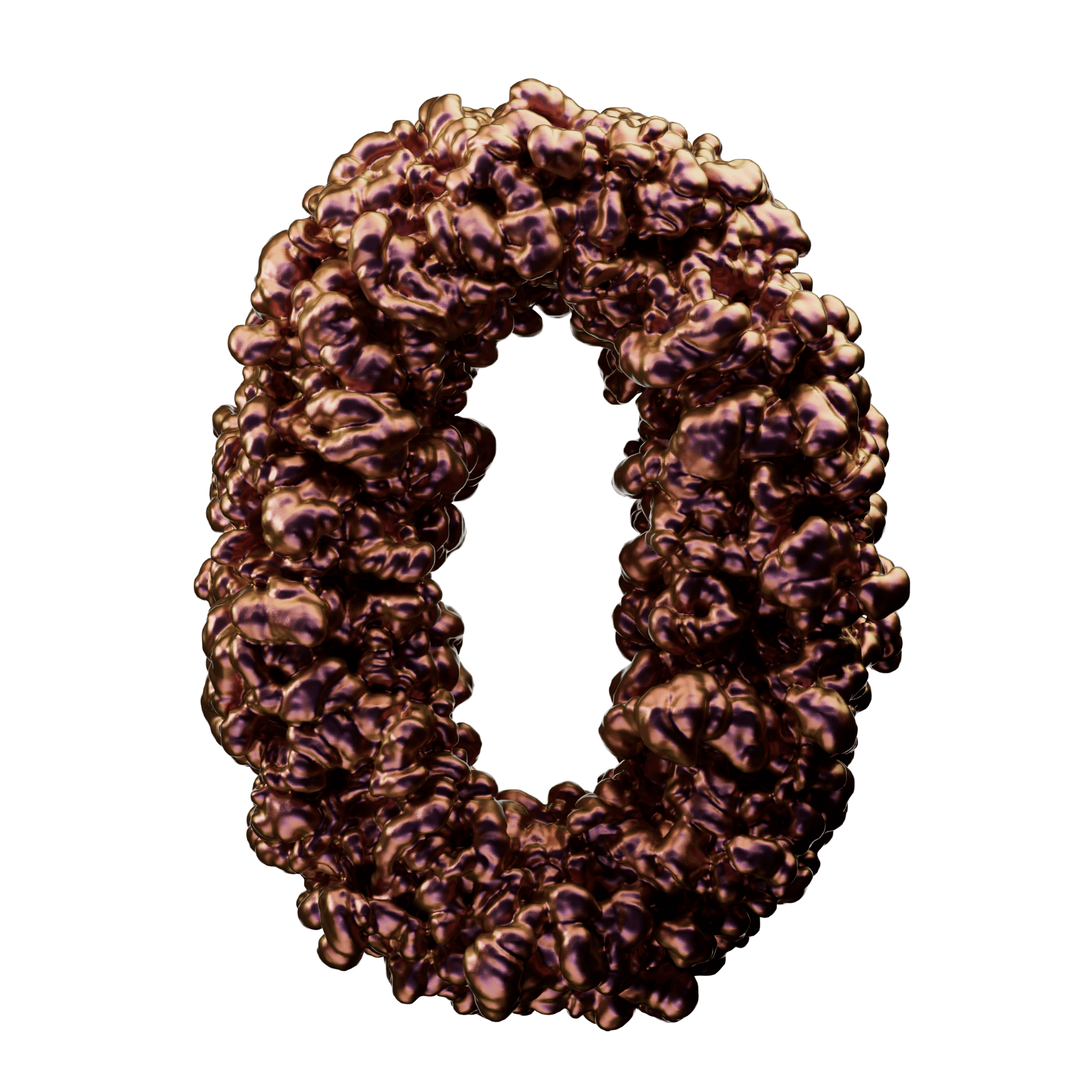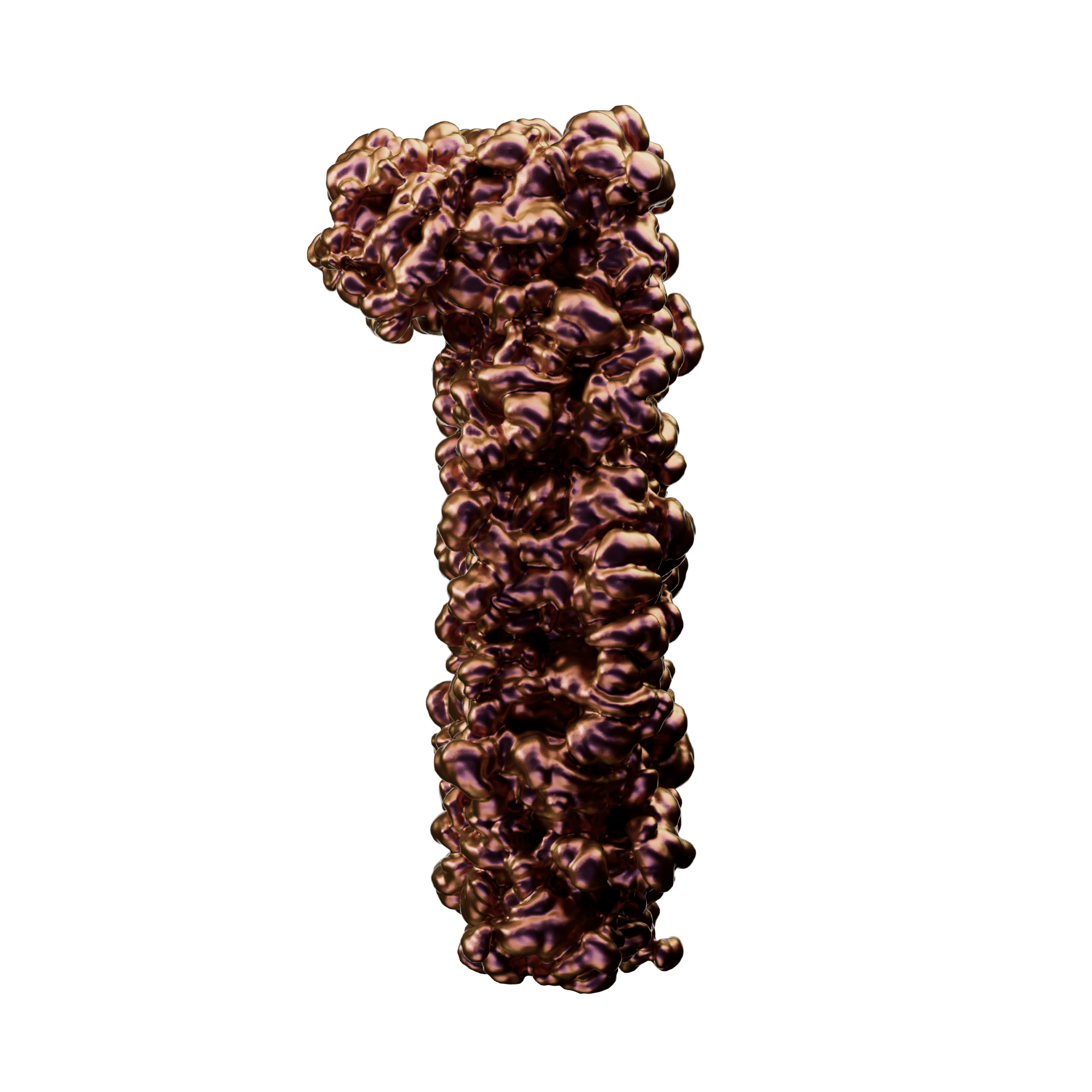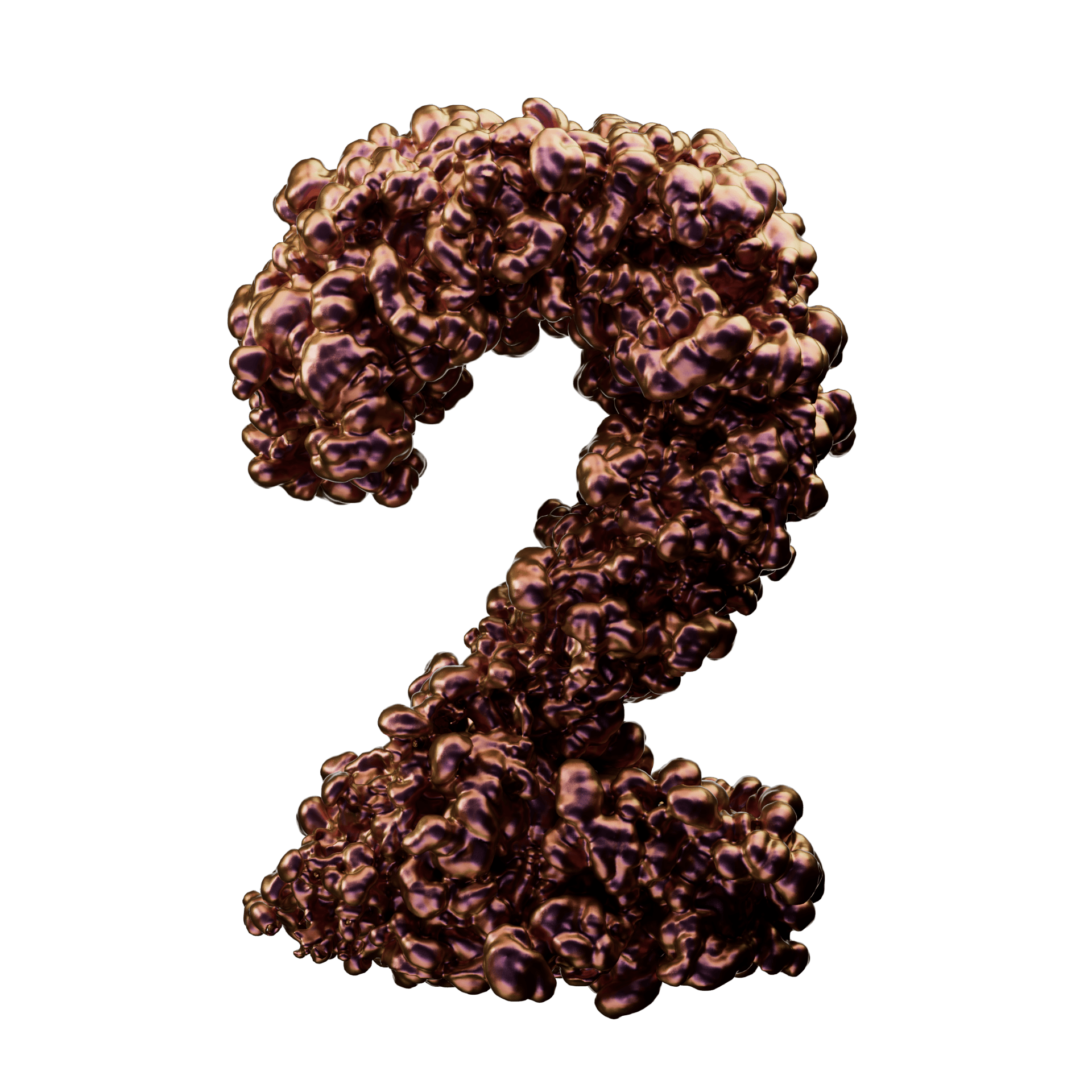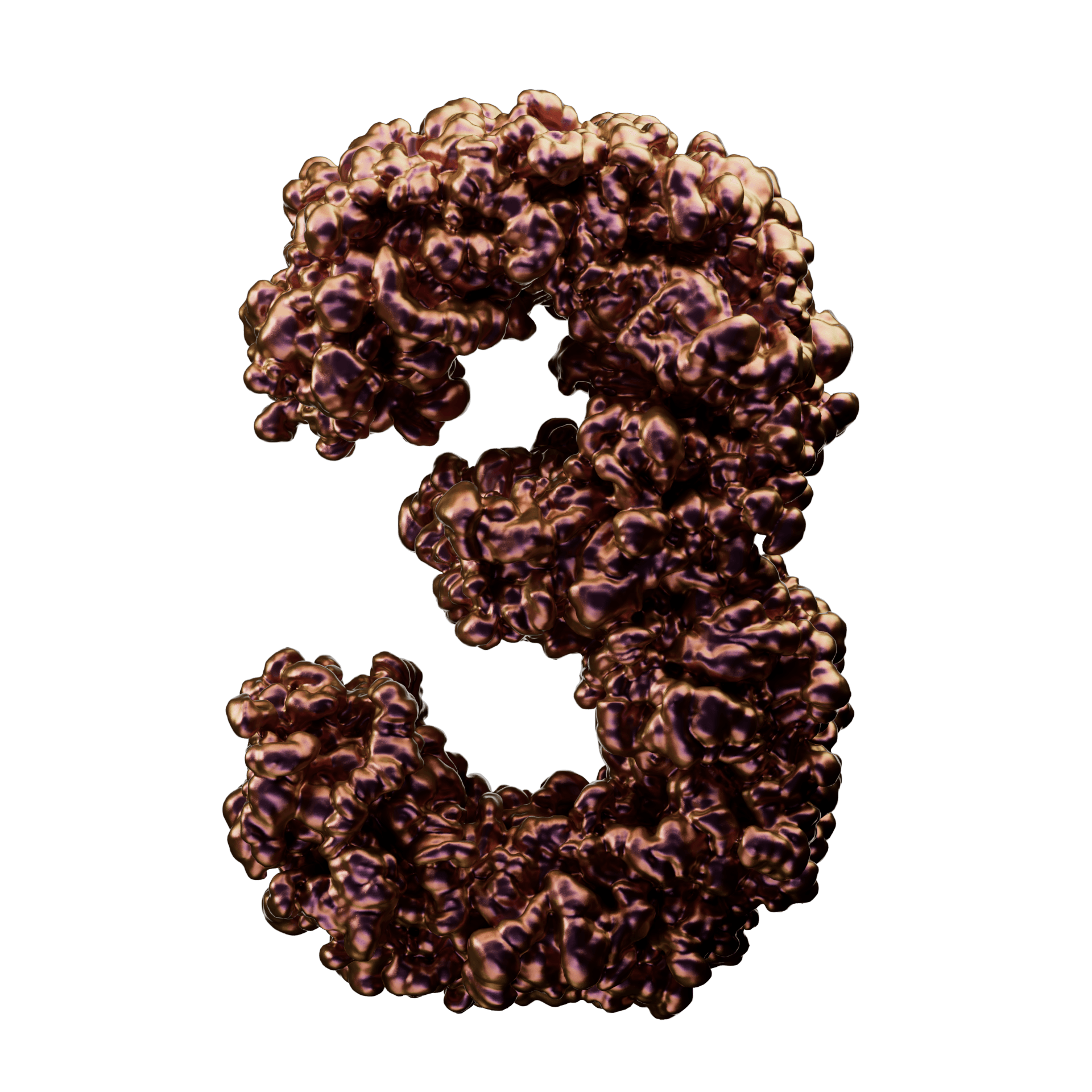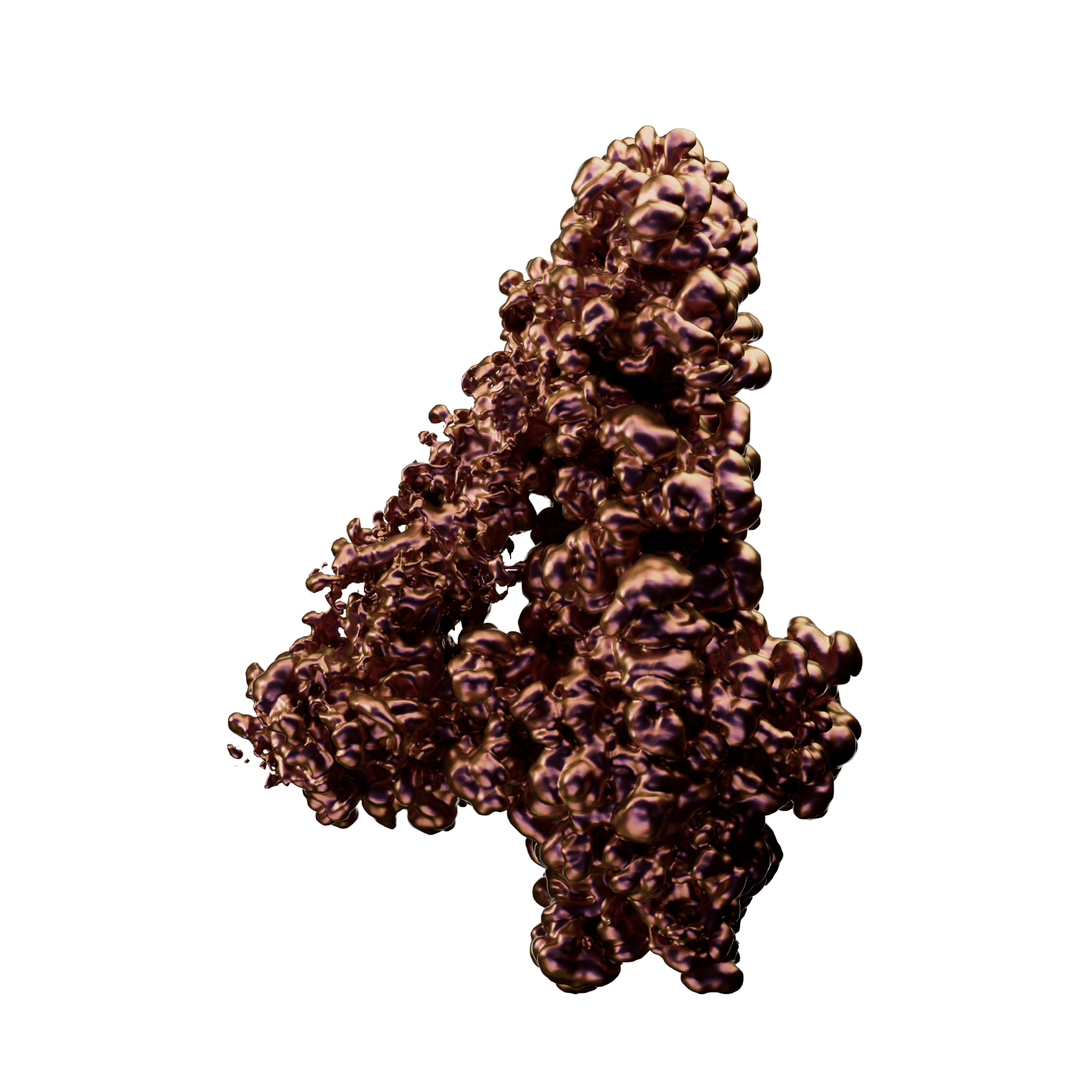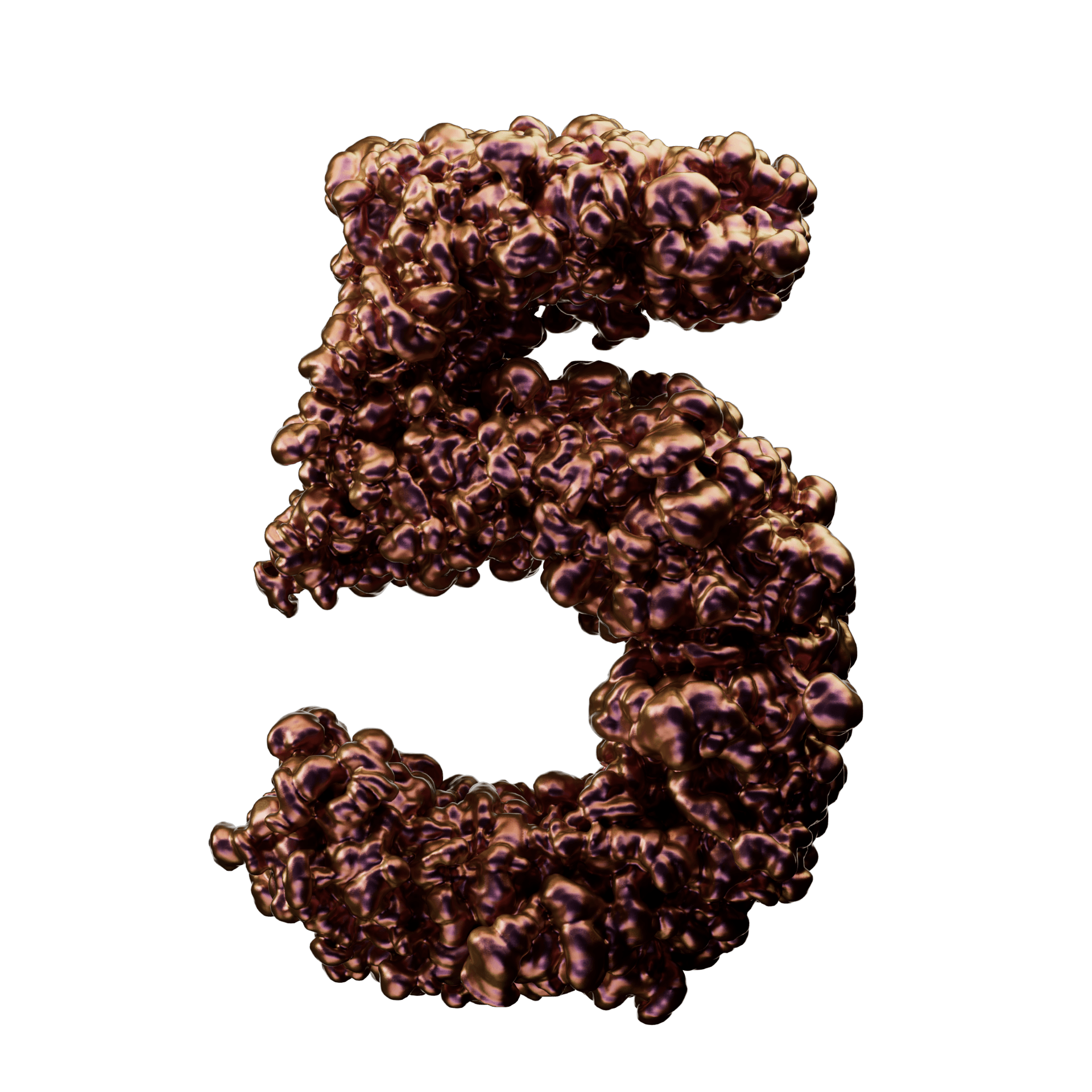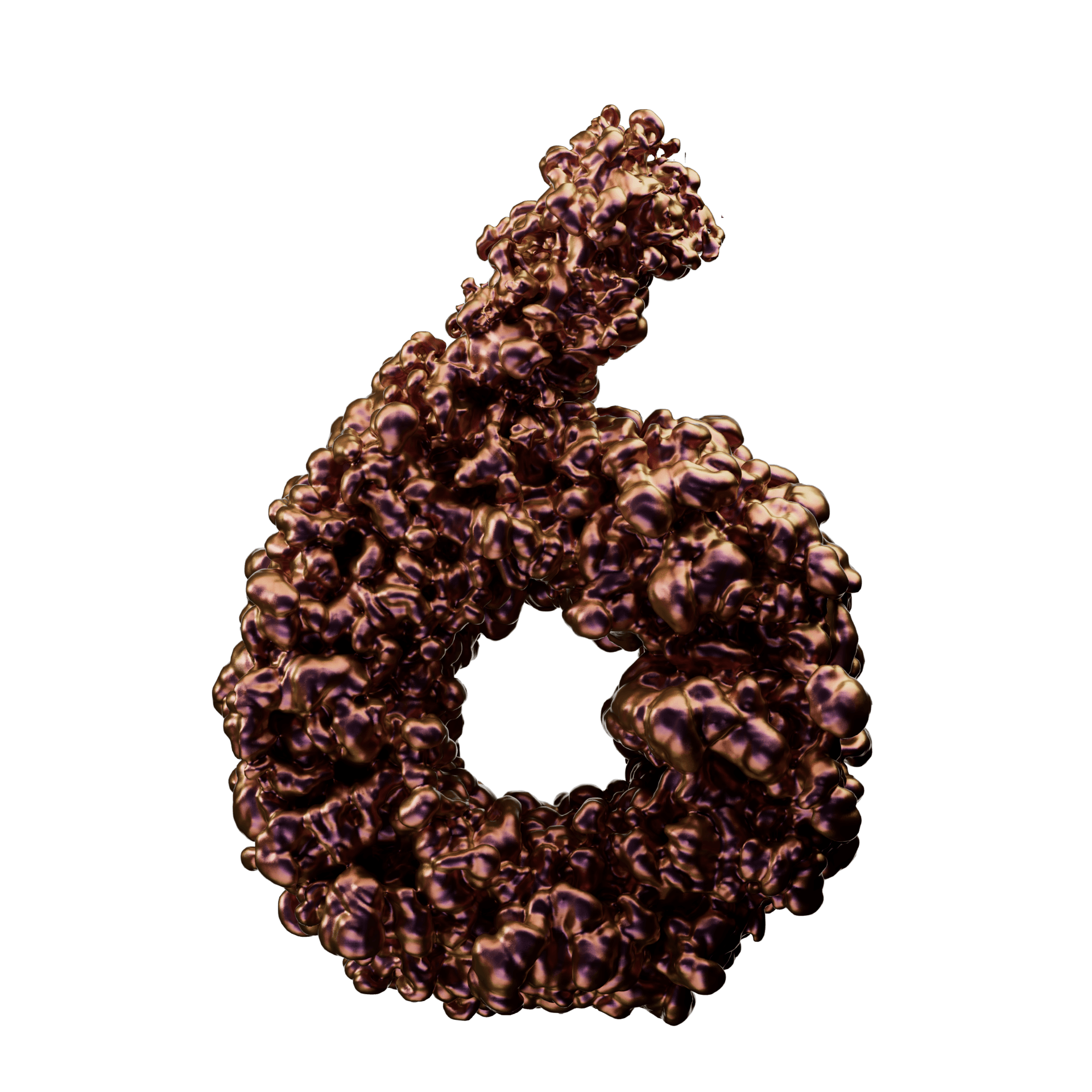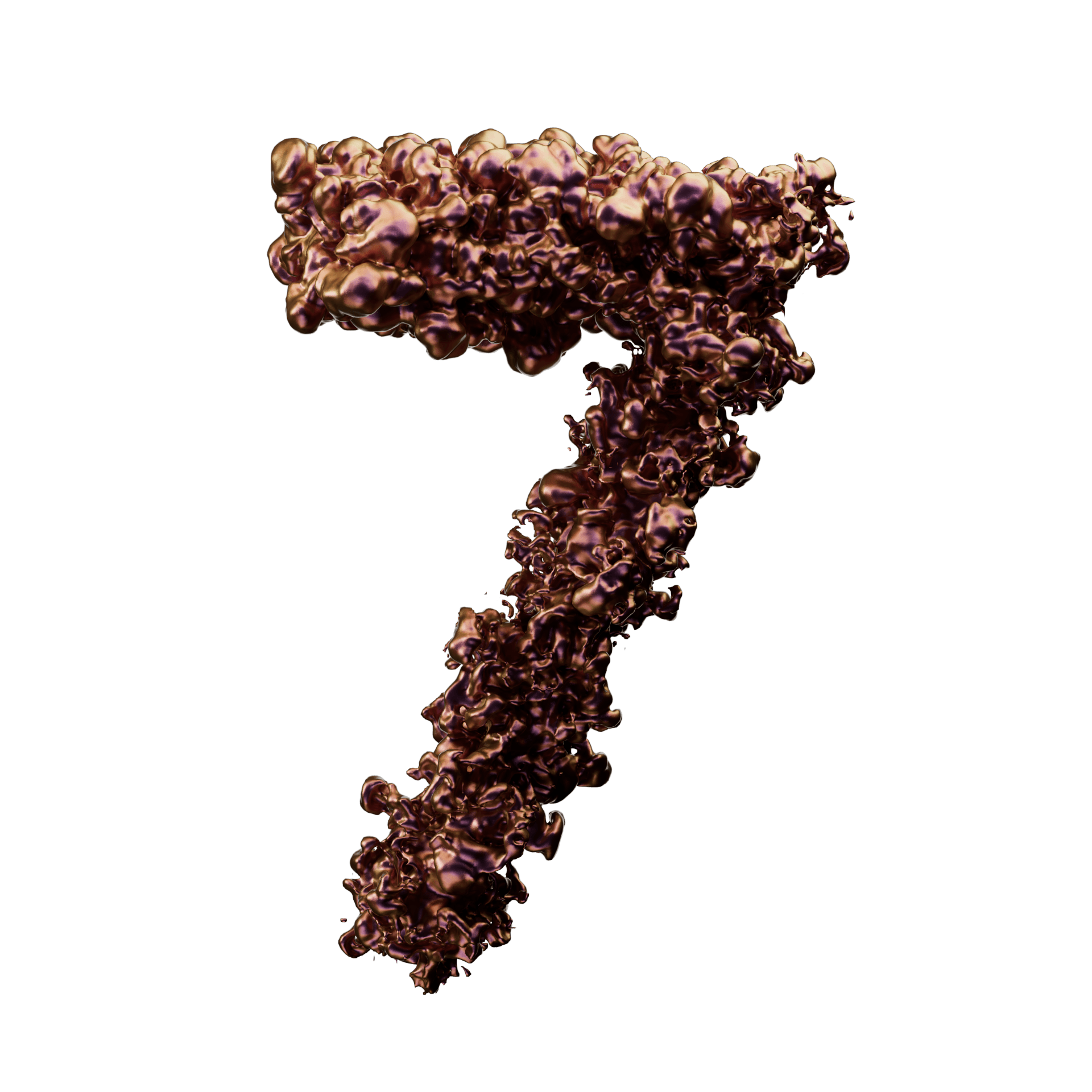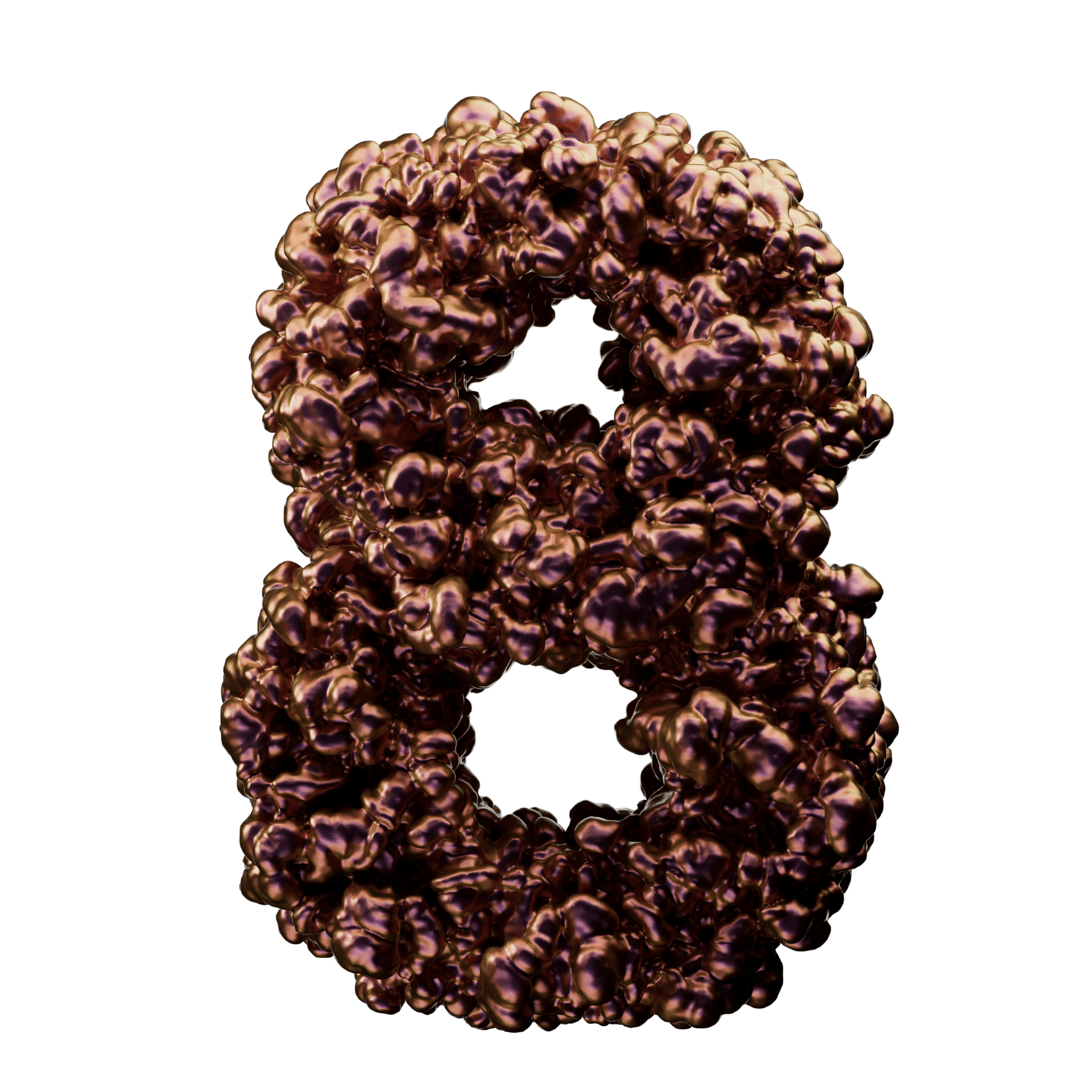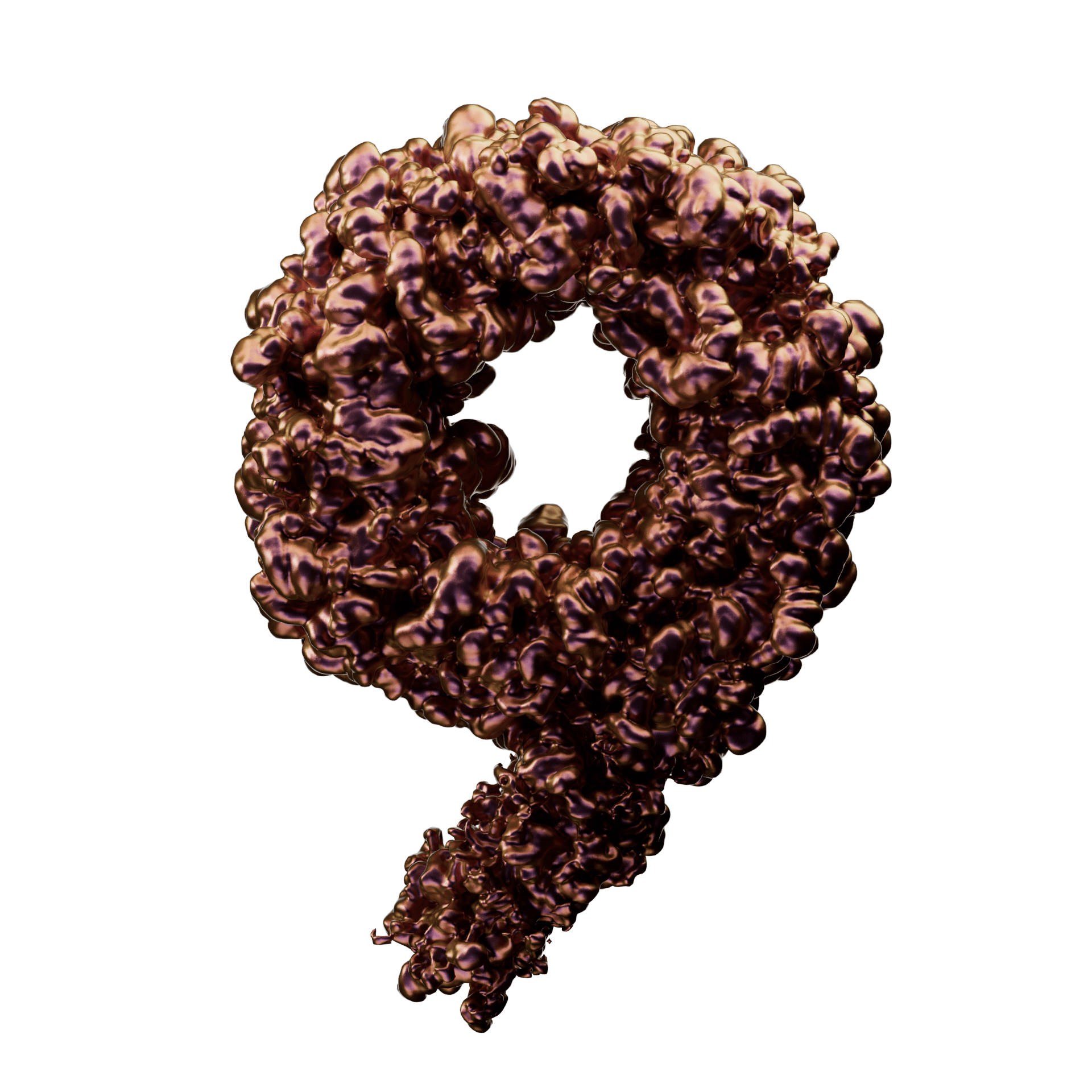
Growth Type
Simulación orgánica, Cinema 4D, X-Particles
Año2024
Growth Type es un alfabeto 3D orgánico: el glifo como colonia. Una simulación de X-Particles nace dentro de la letra y se expande hasta formar una masa nodular densa — cobre iridiscente que vira a púrpura — que conserva la estructura del carácter como andamiaje mientras la superficie adquiere una lógica propia. Hecho con Cinema 4D, X-Particles y Redshift: cuatro vídeos de la letra F y 36 caracteres, de la A a la Z y del 0 al 9.
F
A — Z
Carácter A de Growth Type: letra 3D de cobre iridiscente con textura nodular, nacida de una simulación de X-Particles, sobre fondo negro
Carácter B de Growth Type: letra 3D de cobre iridiscente con textura nodular, nacida de una simulación de X-Particles, sobre fondo negro
Carácter C de Growth Type: letra 3D de cobre iridiscente con textura nodular, nacida de una simulación de X-Particles, sobre fondo negro
Carácter D de Growth Type: letra 3D de cobre iridiscente con textura nodular, nacida de una simulación de X-Particles, sobre fondo negro
Carácter E de Growth Type: letra 3D de cobre iridiscente con textura nodular, nacida de una simulación de X-Particles, sobre fondo negro
Carácter F de Growth Type: letra 3D de cobre iridiscente con textura nodular, nacida de una simulación de X-Particles, sobre fondo negro
Carácter G de Growth Type: letra 3D de cobre iridiscente con textura nodular, nacida de una simulación de X-Particles, sobre fondo negro
Carácter H de Growth Type: letra 3D de cobre iridiscente con textura nodular, nacida de una simulación de X-Particles, sobre fondo negro
Carácter I de Growth Type: letra 3D de cobre iridiscente con textura nodular, nacida de una simulación de X-Particles, sobre fondo negro
Carácter J de Growth Type: letra 3D de cobre iridiscente con textura nodular, nacida de una simulación de X-Particles, sobre fondo negro
Carácter K de Growth Type: letra 3D de cobre iridiscente con textura nodular, nacida de una simulación de X-Particles, sobre fondo negro
Carácter L de Growth Type: letra 3D de cobre iridiscente con textura nodular, nacida de una simulación de X-Particles, sobre fondo negro
Carácter M de Growth Type: letra 3D de cobre iridiscente con textura nodular, nacida de una simulación de X-Particles, sobre fondo negro
Carácter N de Growth Type: letra 3D de cobre iridiscente con textura nodular, nacida de una simulación de X-Particles, sobre fondo negro
Carácter O de Growth Type: letra 3D de cobre iridiscente con textura nodular, nacida de una simulación de X-Particles, sobre fondo negro
Carácter P de Growth Type: letra 3D de cobre iridiscente con textura nodular, nacida de una simulación de X-Particles, sobre fondo negro
Carácter Q de Growth Type: letra 3D de cobre iridiscente con textura nodular, nacida de una simulación de X-Particles, sobre fondo negro
Carácter R de Growth Type: letra 3D de cobre iridiscente con textura nodular, nacida de una simulación de X-Particles, sobre fondo negro
Carácter S de Growth Type: letra 3D de cobre iridiscente con textura nodular, nacida de una simulación de X-Particles, sobre fondo negro
Carácter T de Growth Type: letra 3D de cobre iridiscente con textura nodular, nacida de una simulación de X-Particles, sobre fondo negro
Carácter U de Growth Type: letra 3D de cobre iridiscente con textura nodular, nacida de una simulación de X-Particles, sobre fondo negro
Carácter V de Growth Type: letra 3D de cobre iridiscente con textura nodular, nacida de una simulación de X-Particles, sobre fondo negro
Carácter W de Growth Type: letra 3D de cobre iridiscente con textura nodular, nacida de una simulación de X-Particles, sobre fondo negro
Carácter X de Growth Type: letra 3D de cobre iridiscente con textura nodular, nacida de una simulación de X-Particles, sobre fondo negro
Carácter Y de Growth Type: letra 3D de cobre iridiscente con textura nodular, nacida de una simulación de X-Particles, sobre fondo negro
Carácter Z de Growth Type: letra 3D de cobre iridiscente con textura nodular, nacida de una simulación de X-Particles, sobre fondo negro
0 — 9
Carácter 0 de Growth Type: letra 3D de cobre iridiscente con textura nodular, nacida de una simulación de X-Particles, sobre fondo negro
Carácter 1 de Growth Type: letra 3D de cobre iridiscente con textura nodular, nacida de una simulación de X-Particles, sobre fondo negro
Carácter 2 de Growth Type: letra 3D de cobre iridiscente con textura nodular, nacida de una simulación de X-Particles, sobre fondo negro
Carácter 3 de Growth Type: letra 3D de cobre iridiscente con textura nodular, nacida de una simulación de X-Particles, sobre fondo negro
Carácter 4 de Growth Type: letra 3D de cobre iridiscente con textura nodular, nacida de una simulación de X-Particles, sobre fondo negro
—La letra: el andamiaje estructural de cada carácter condiciona la distribución nodular resultante en los 36 caracteres (A–Z y 0–9)
—El encuadre: letra F completa, como volumen colonizado
—Macro — superficie nodular sin referencia tipográfica
—Detalle iridiscente — textura y material como protagonistas
—No explorada: densidad de colonización variable dentro del mismo volumen — el umbral se mantuvo constante